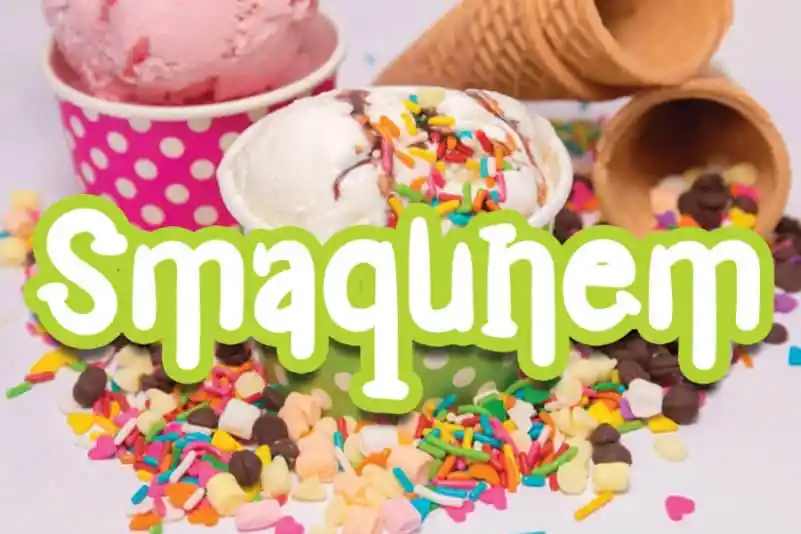
Smaqunem Display Font é uma elegante fonte serif que adiciona um toque único a qualquer design, seja ele digital ou impresso. Desenvolvida pela equipe do andikastudio, essa fonte se destaca por sua personalidade e originalidade. Com cores vibrantes e uma aparência amigável, ela enriquece designs variados com facilidade. A única limitação é a imaginação do designer em criar novas formas para esse charmoso tipo. Sua versatilidade e sofisticação tornam Smaqunem Display Font o elemento perfeito para qualquer projeto que precise de um toque diferenciado, seja ele digital ou impresso no papel. Experimente essa fonte e deixe seu design brilhar com a identidade única da Smaqunem.